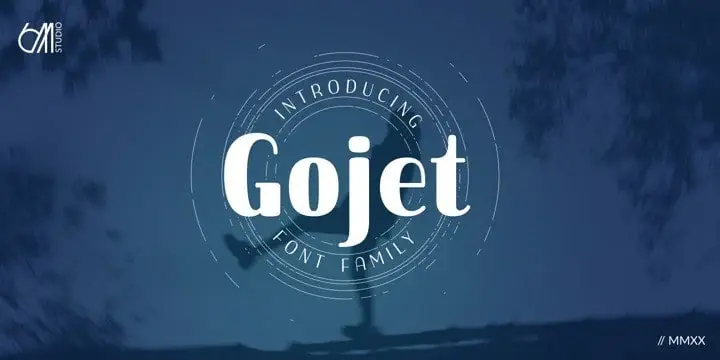
A Gojet Sans Serif é uma família de fontes geometricas sem serif que traz elementos únicos para um toque distintivo. Ela oferece uma aparência limpa e moderna, mantendo também alguns tons retro, criando um design sofisticado simples que combina perfeitamente em textos, headlines ou logotipos. Gojet está disponível nas seis opções de peso, tornando-a extremamente versátil para uso em vários formatos e contextos. Experimentar diferentes pesos é a melhor estratégia para fazer seu projeto ainda mais atraente e chamativo. Essa fonte é perfeita para designers que buscam um equilíbrio elegante entre simplicidade e personalização, sem sacrificar a funcionalidade ou a versatilidade.